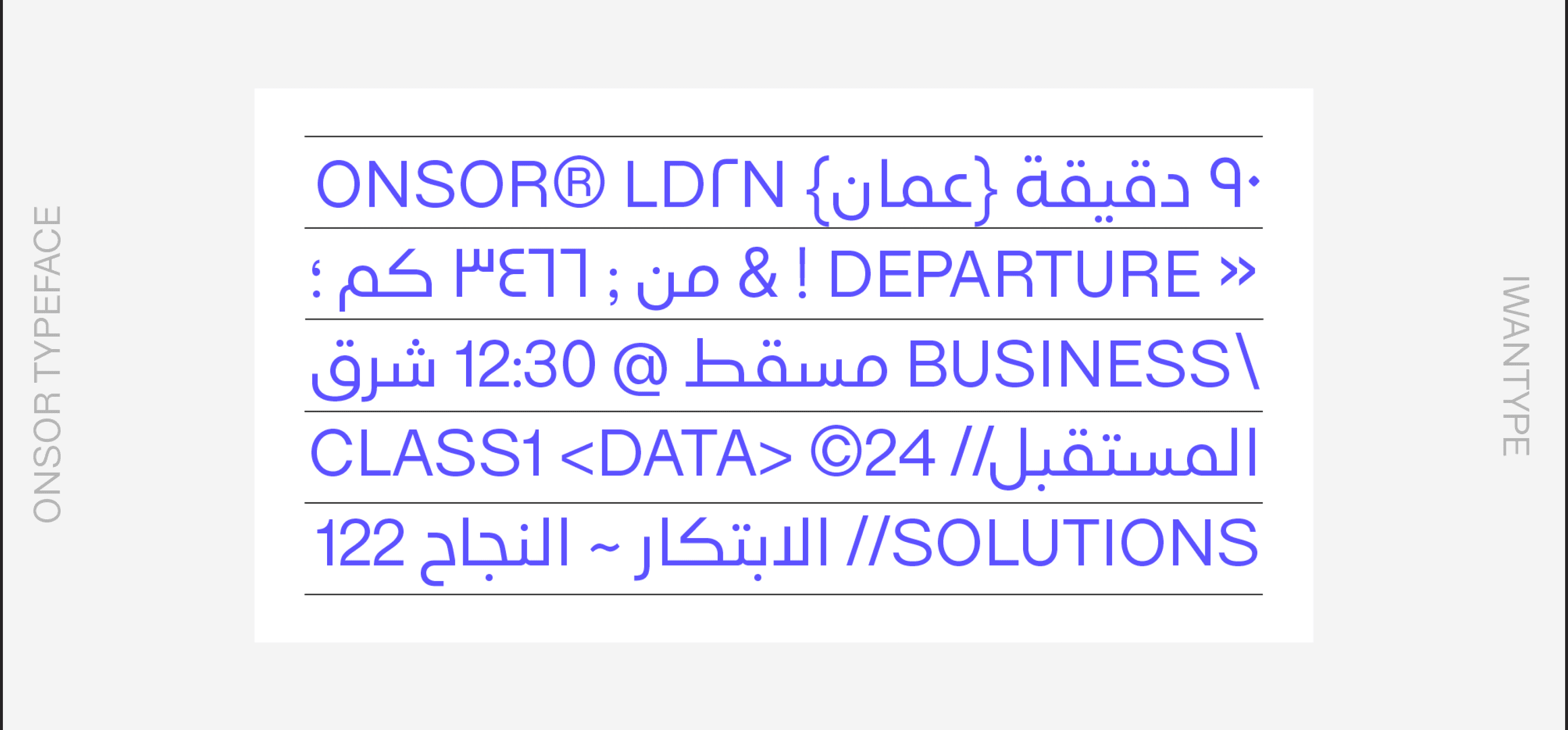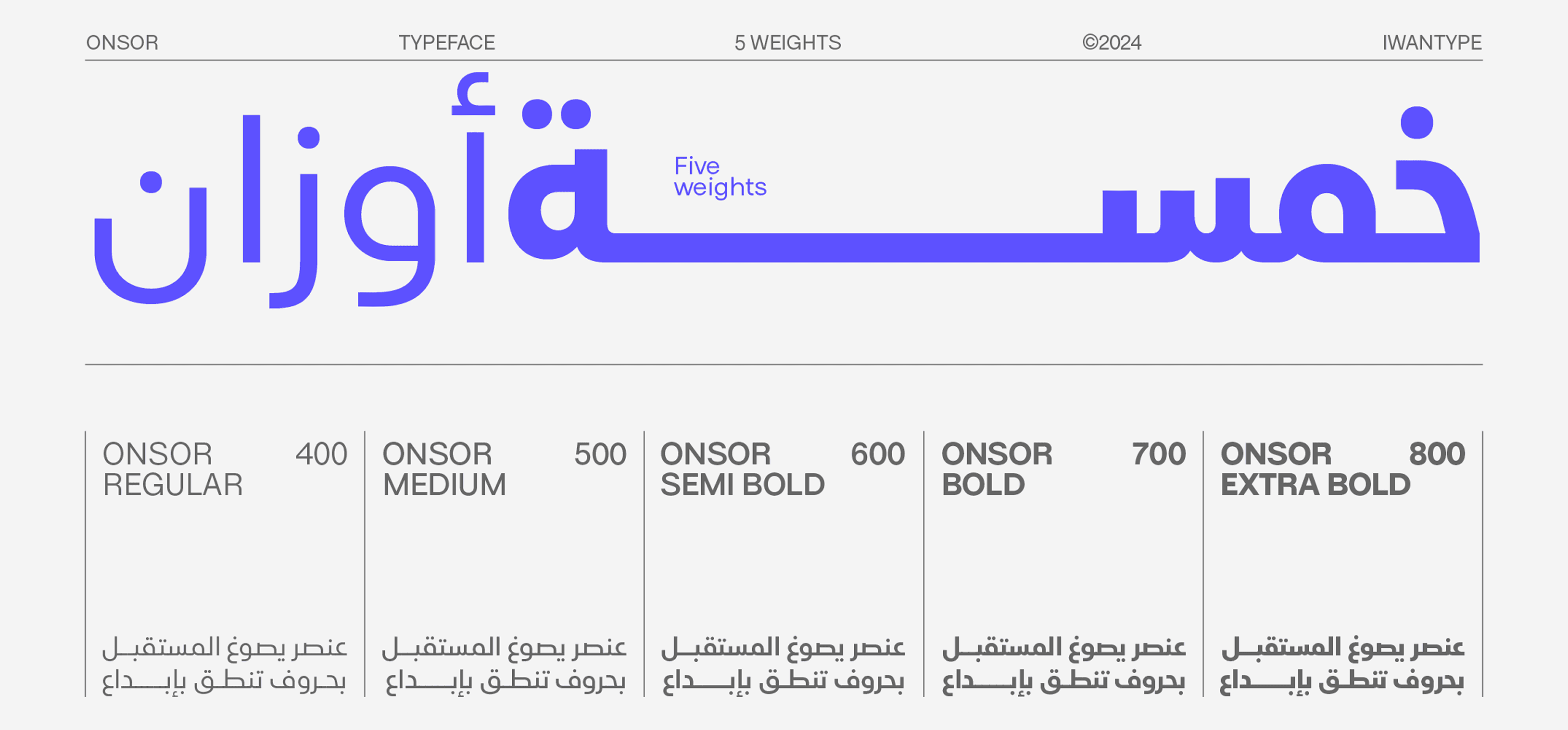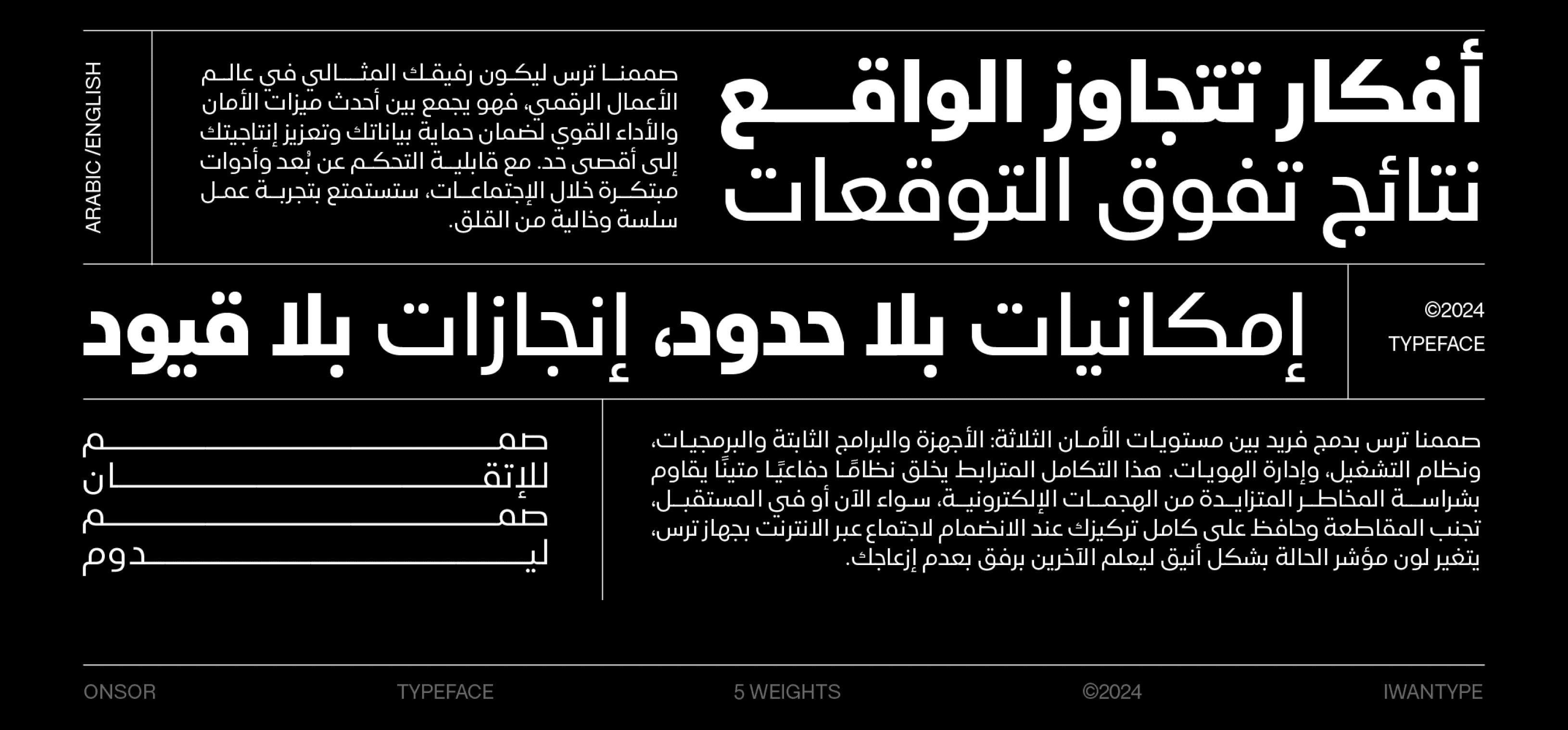
خطًا طباعيًا مخصصًا لشركة عنصر، يجمع بين جماليات الخط العربي وبساطة الخط اللاتيني. يهدف هذا الخط إلى تعزيز هوية الشركة وعكس روحها الهندسية. يتكون الخط من خمسة أوزان مختلفة لتلبية متطلبات التصميم المتنوعة، مما يمنحه مرونة عالية في الاستخدام.”